英文艺术字体在线转换的发展有着漫长的变迁史,通过长时间的艺术积累和技术沉淀,目前的在线转换的英文字体变得更加深邃,具有鉴赏能力的审美爱好者表示,一些在线转换的字体有着深厚的美术功底,设计方式得当,那么英文艺术字体在线转换后有哪些妙用呢?
关于电影海报也是艺术字的主打区域,有很多电影海报的艺术字也是做的非常优秀的,举例来看,如警察故事、让子弹飞,画面之外的艺术字体也是不可或缺的一部分,我们必须要把艺术字做的也非常突出,因为我们看到英文艺术字体在线转换后的电影海报的时候,第一感觉第一印象就是艺术字,这个艺术字是什么样的字,在表达什么?在告诉我们什么?艺术字必须和它的画面背景相互协调,相互映衬,从而表现出一个完整的海报主题。
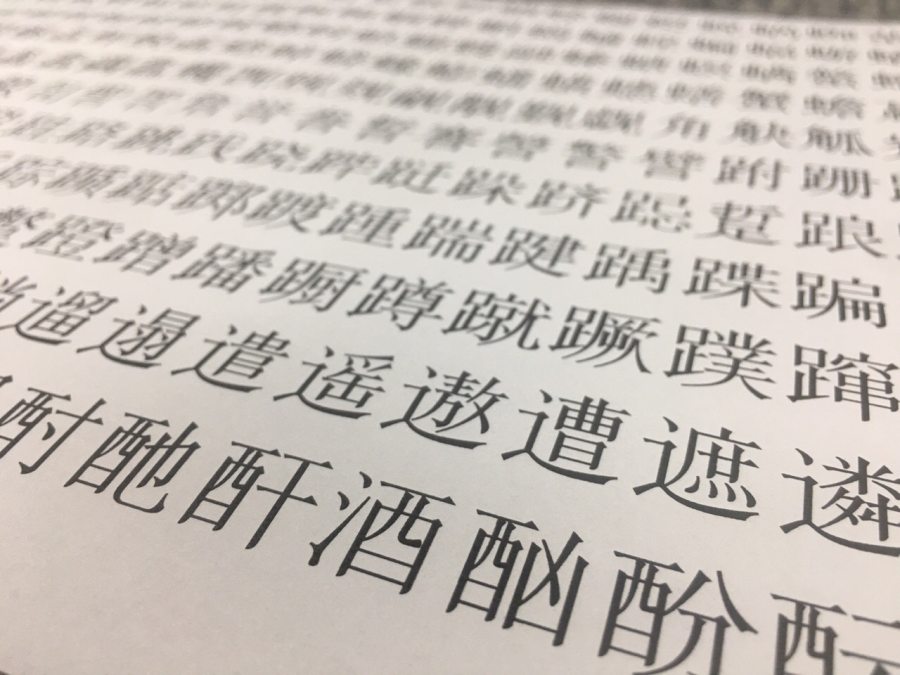
可以想象一下,如果英文艺术字体在线转换非常突出,背景非常炫目,非常酷,但是它的艺术字做的很一般,或者是直接套用了一个字库艺术字,那它所表现出来的整体性和完整性就没有那么强烈,让我们把艺术字的特效、笔画完全和电影的情节吻合,电影画面和海报画面能够相互融为一体,这个海报才是最完美的、准确的。
由于不同的英文艺术字体在线转换能够展示出不同的艺术字体设计方法,甚至能够表示出设计者的情感,印品字库中的字体一些为对祖国的大爱,一些为对行业的热爱,一些是对个人情感的归纳和沉淀。